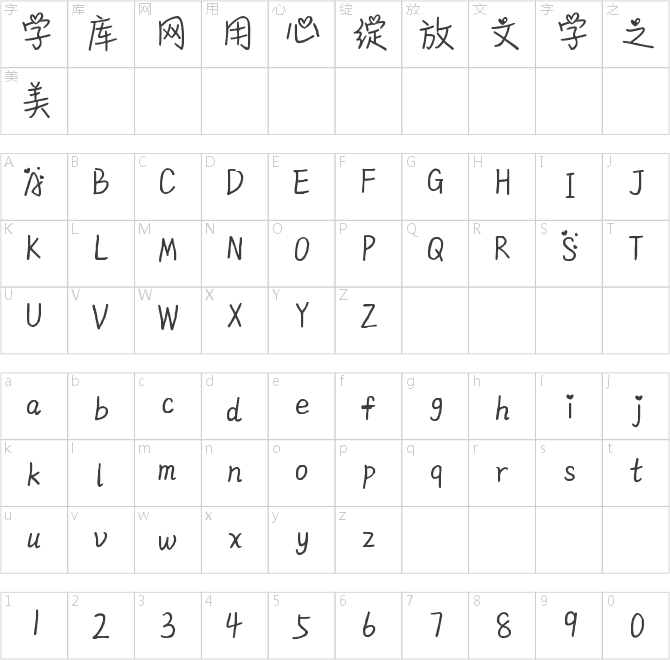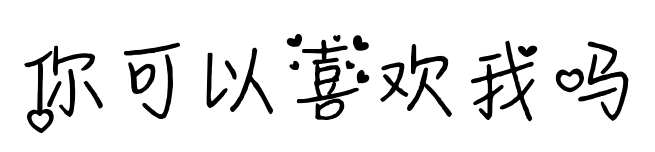
字體名稱: 你可以喜歡我嗎
你可以喜歡我嗎
拜托啦,要喜歡我,超級喜歡的那種。
你可以喜歡我嗎字體字庫是一款讓人賞心悅目、百看不厭的中文字體,適合各類廣告和產(chǎn)品包裝設(shè)計應(yīng)用,字體大小6.38MB,格式為ttf字體,上傳用戶是喜歡戳爺,作者/版權(quán)方為義啟字庫